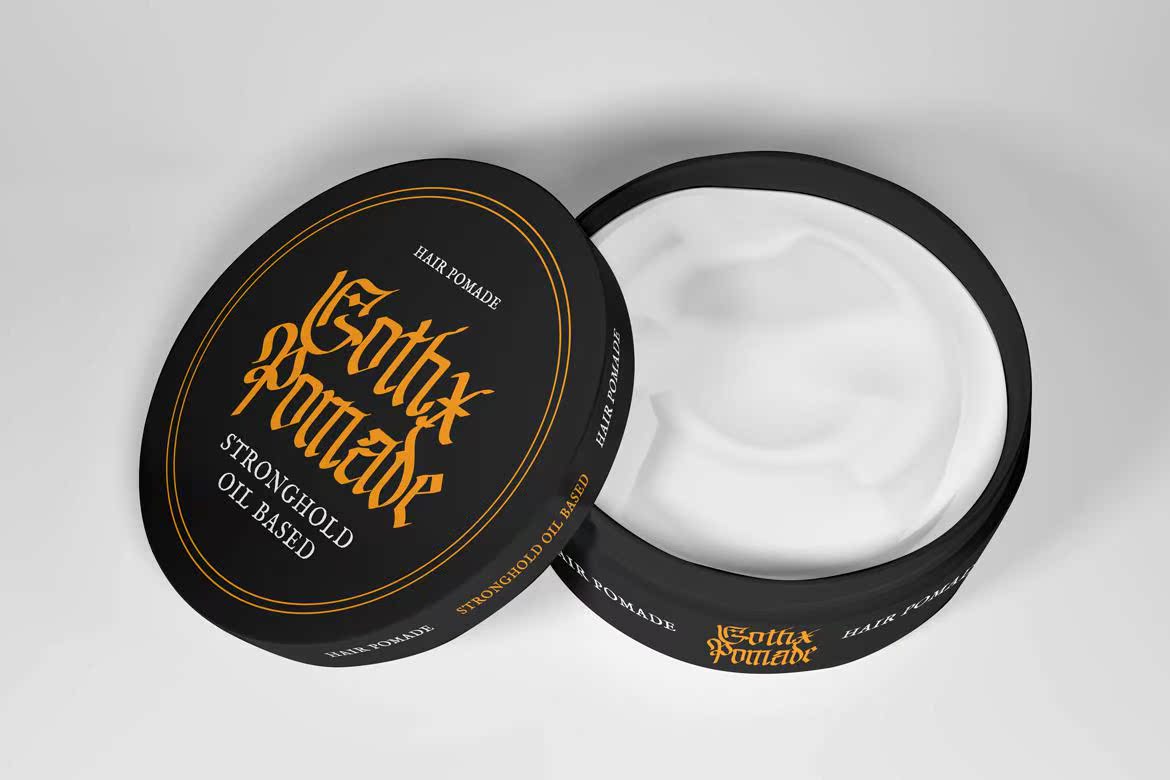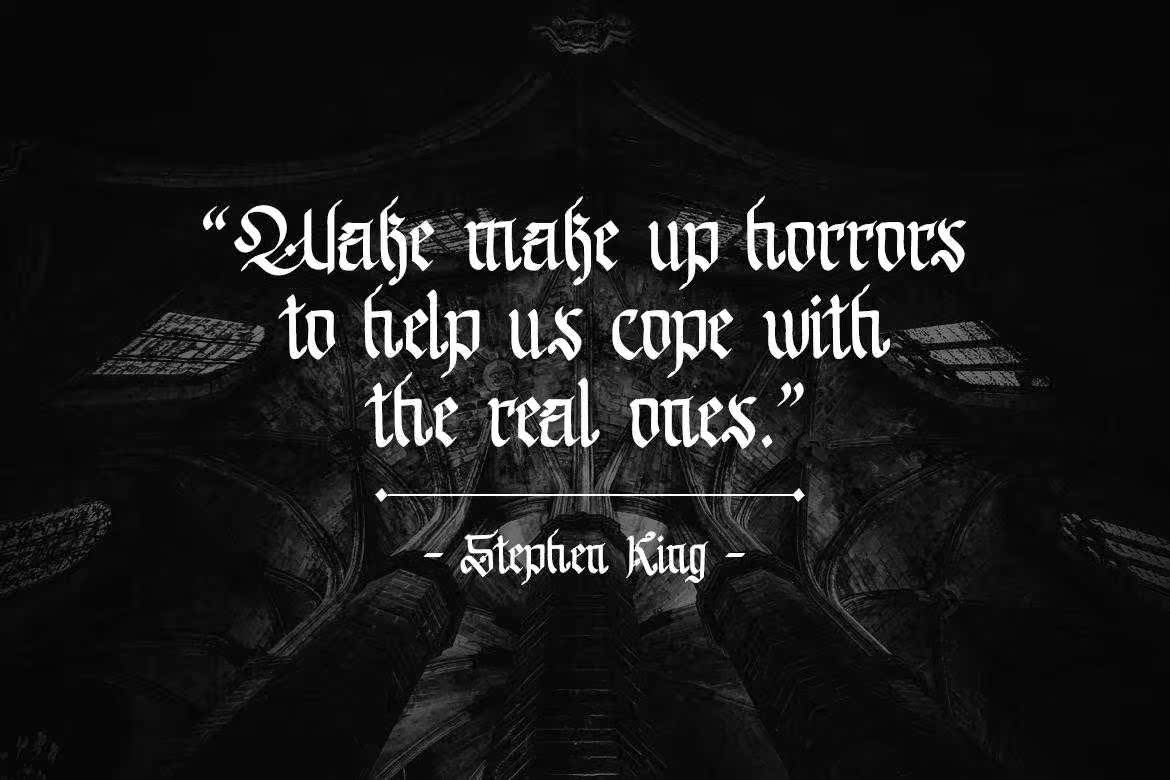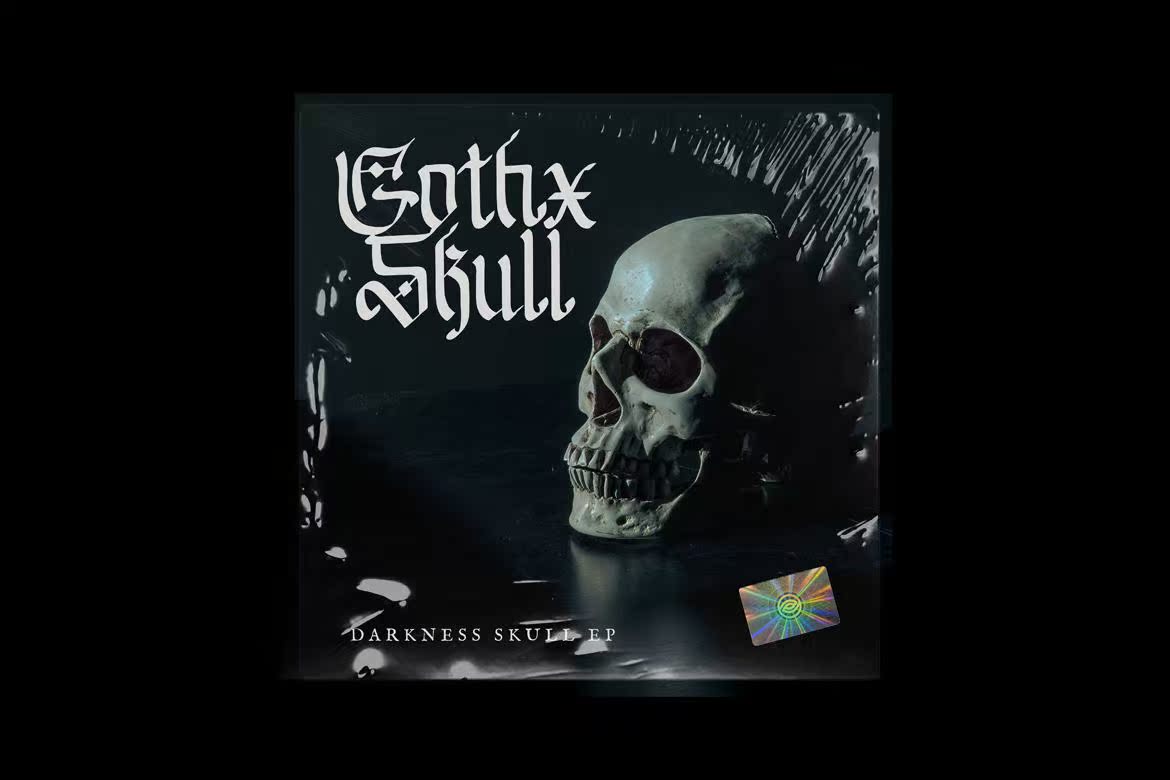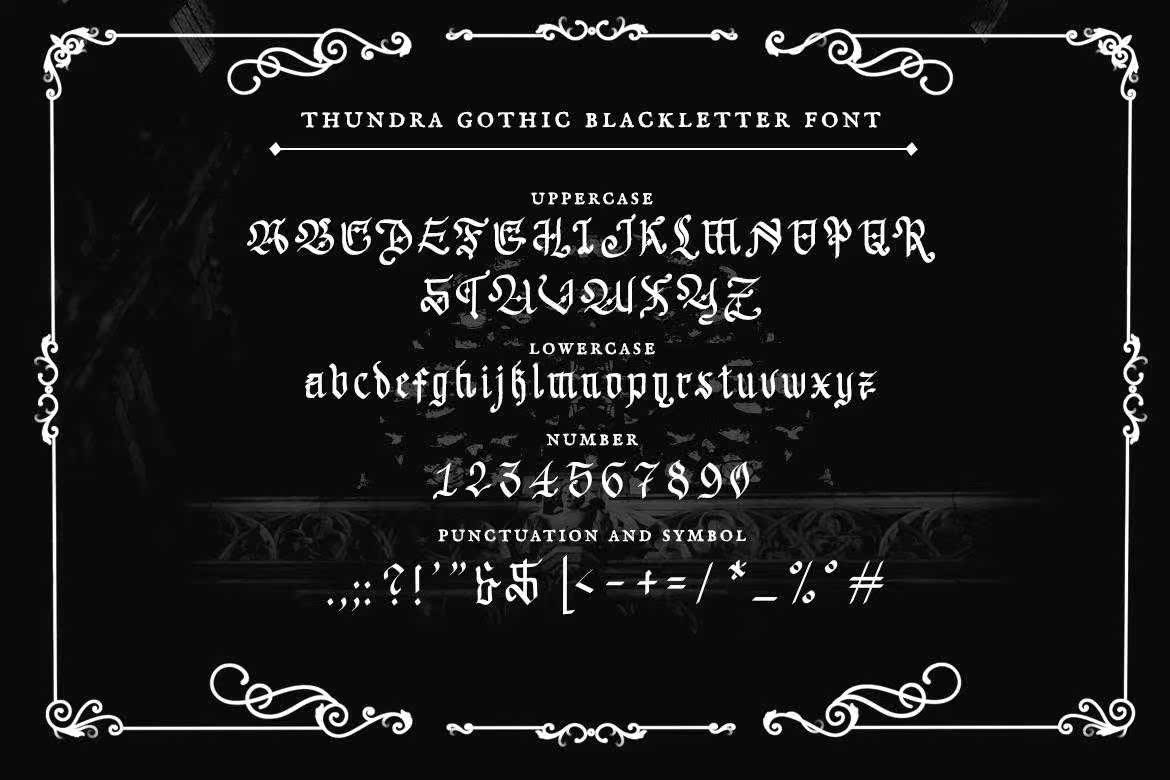
Thundra–黑体字字体-印刷体免费字体免费印刷体 15166
Thundrais SimpleandLegant Blackletter字体。将此字体添加到您的每一项创作中,并注意它将如何让它们脱颖而出!Thundrais SimpleandLegant Blackletter字体。将此字体添加到您的每一项创作中,并注意它将如何让它们脱颖而出!